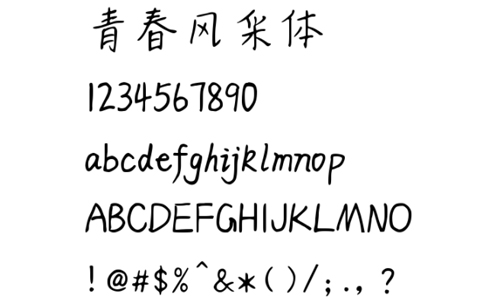
青春風(fēng)采體字體是思雨字庫推出的一款硬筆手寫字體,本字體是在國家標(biāo)準(zhǔn)簡體字庫GB2312所包含6763漢字的基礎(chǔ)上,又增加了近200常用字,已經(jīng)覆蓋了大陸99.75%的漢字使用頻率,足以滿足日常需求。“青春沒有失敗,只要亮出風(fēng)采。——青春風(fēng)采體”,歡迎喜歡的朋友前來下載使用。